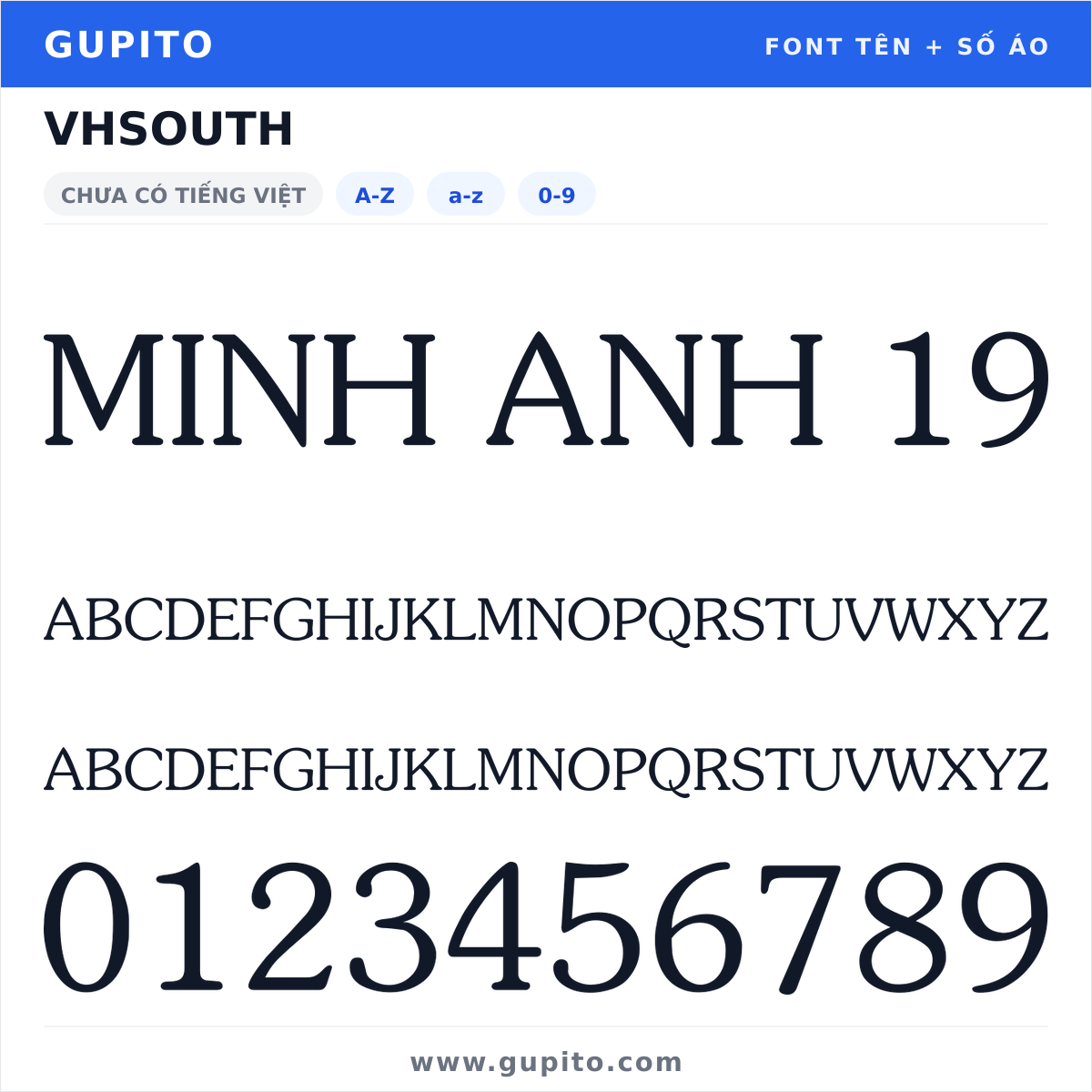
.VnSouthernH
.VnSouthernH · Font VHSOUTH in tên số áo bóng đá, áo lớp, quà tặng · chữ đậm chân
Font VHSOUTH với nét chữ đậm, chân chữ có chân, phù hợp in tên áo bóng đá, áo lớp, áo đội, quà tặng. Có bảng số 0-9. Bộ chữ .VnSouthernH dùng để in chuyển nhiệt lên áo đấu, áo lớp, áo nhóm và đồ thể thao theo yêu cầu. Kiểu dáng: chữ đậm chân. Font dùng cho chữ không dấu và số áo. Có đủ bộ chữ số để in số áo. Từ khoá liên quan: font vhsouth, font in ten ao, font in so ao, font ao bong da, font ao lop, font in chuyen nhiet, font co bang so, font chu dam.